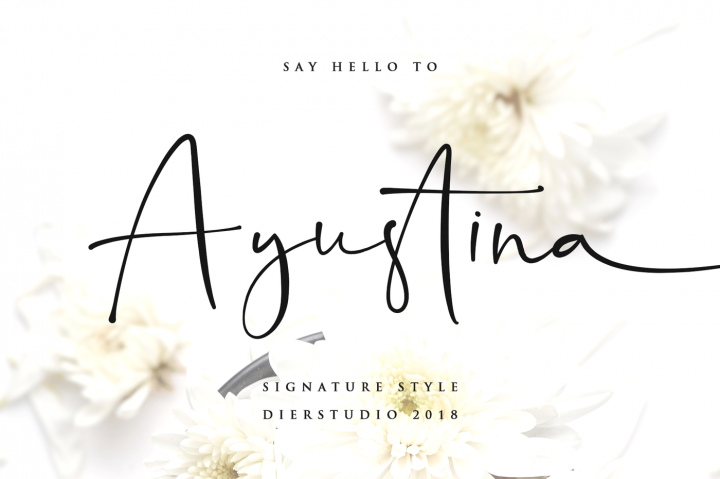
Ayustina Signature Font – Fonte Grátis
Ayustina Signature Font
Venha conhecer a Ayustina Signature Font, uma fonte script que reflete a elegância moderna de um estilo de escrita natural. Introduzida pelo designer zziplex, essa fonte é projetada para imitar perfeitamente a delicadeza e as nuances da mão humana. Ideal para uma variedade de usos, como desenhos de marca, logotipos, designs para casamentos, posts nas redes sociais, anúncios, embalagens de produtos, design dos produtos, etiquetas, fotografia e até mesmo marcas em imagens, a Ayustina se destaca por sua capacidade única. Sua semelhança com um estilo de escrita natural faz dela uma opção excelente para quem busca expressar personalidade e originalidade em seus projetos gráficos. Experimente a Ayustina Font e dê vida à sua ideia através de um design que impressionará seus destinatários.